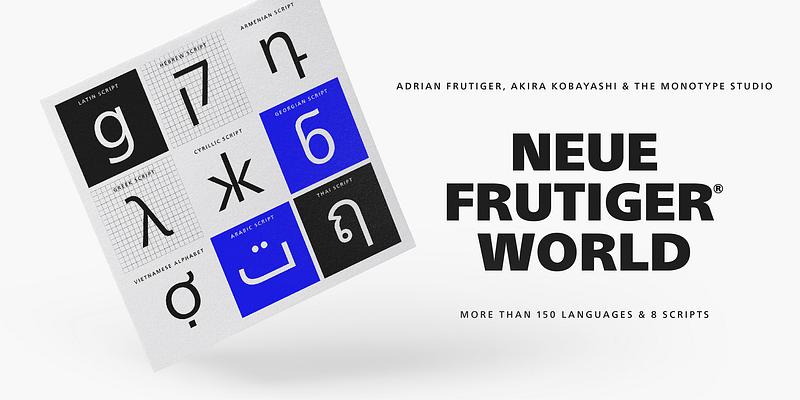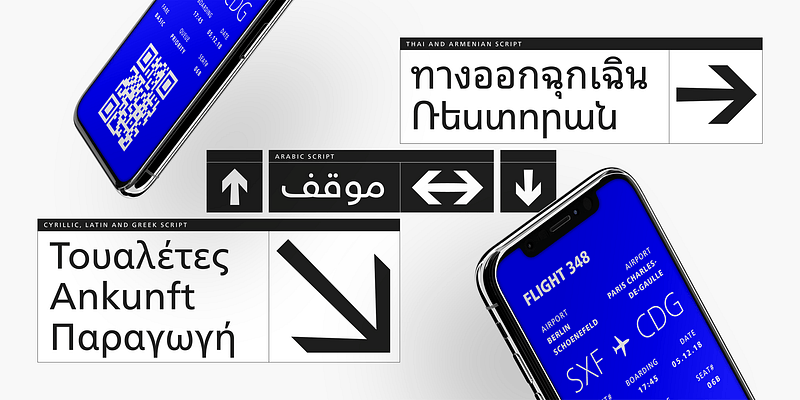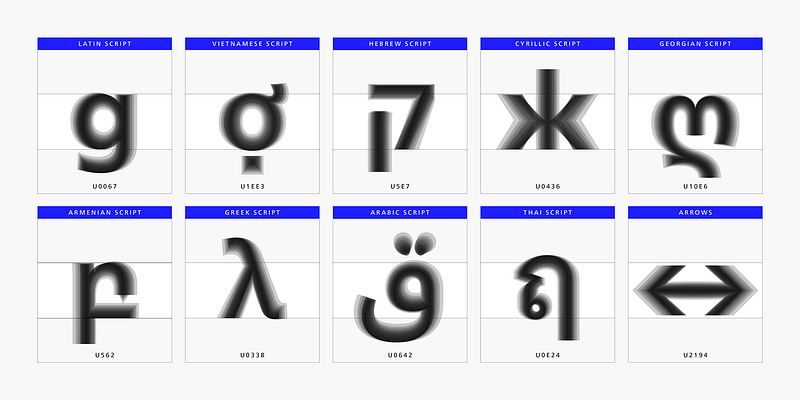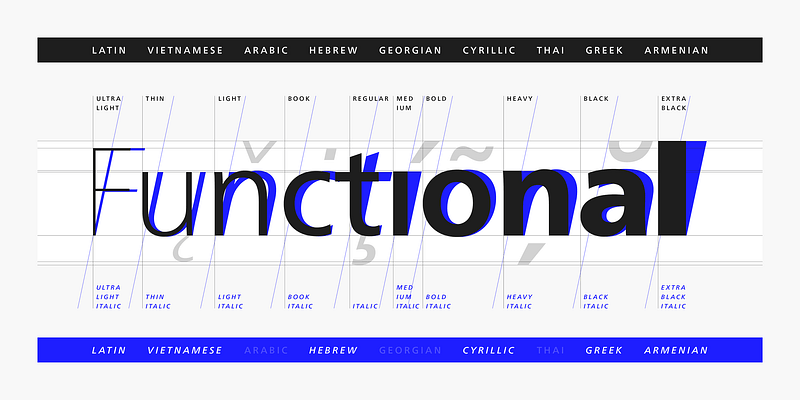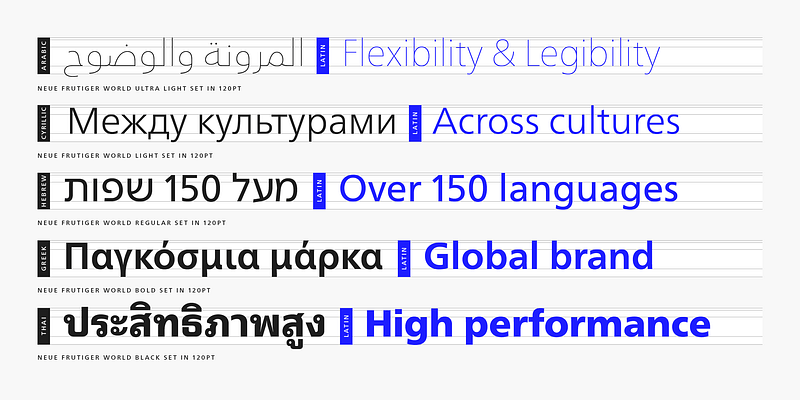
Neue Frutiger World ist für den weltweiten Einsatz konzipiert und bietet eine beeindruckende Auswahl von zehn Schriftstärken – von Ultra Light bis Extra Black – mit passenden Kursivschriften. Sie verkörpert die gleiche Wärme und Klarheit wie Adrian Frutigers Original-Design, ermöglicht es Marken jedoch, ihre visuelle Identität beizubehalten und sprachunabhängig in einem einheitlichen Tonfall zu kommunizieren. Neue Frutiger World unterstützt über 150 Sprachen und Schriften, darunter Latein, Griechisch, Kyrillisch, Georgisch, Armenisch, Hebräisch, Arabisch, Thailändisch und Vietnamesisch. „Vor der Einführung der Neue Frutiger World war es für westliche Marken nicht einfach, Schriftfamilien in Arabisch, Hebräisch, Thailändisch und Vietnamesisch zu finden, die zu ihrer lateinischen Schrift passten“, sagt Akira Kobayashi, Type Director bei Monotype und verantwortlich für das Projekt Neue Frutiger World. „Sie finden zwar eine ausdrucksstärkere Schrift, aber es gibt keine Garantie dafür, dass die fette Version der nicht-lateinischen Schriftfamilie mit der fetten Version in ihrer Lateinschrift übereinstimmt. Die Neue Frutiger World bietet eine bessere Lösung.“ Neben ihrer sprachlichen Vielseitigkeit eignet sich die Neue Frutiger World hervorragend für verschiedene Umgebungen – für Branding und Corporate Identity, Werbung, Beschilderung, Wegweiser, Print und digitale Umgebungen. Die Schriften der Neue Frutiger World lassen sich mit den CJK-Schriften von Monotype kombinieren.